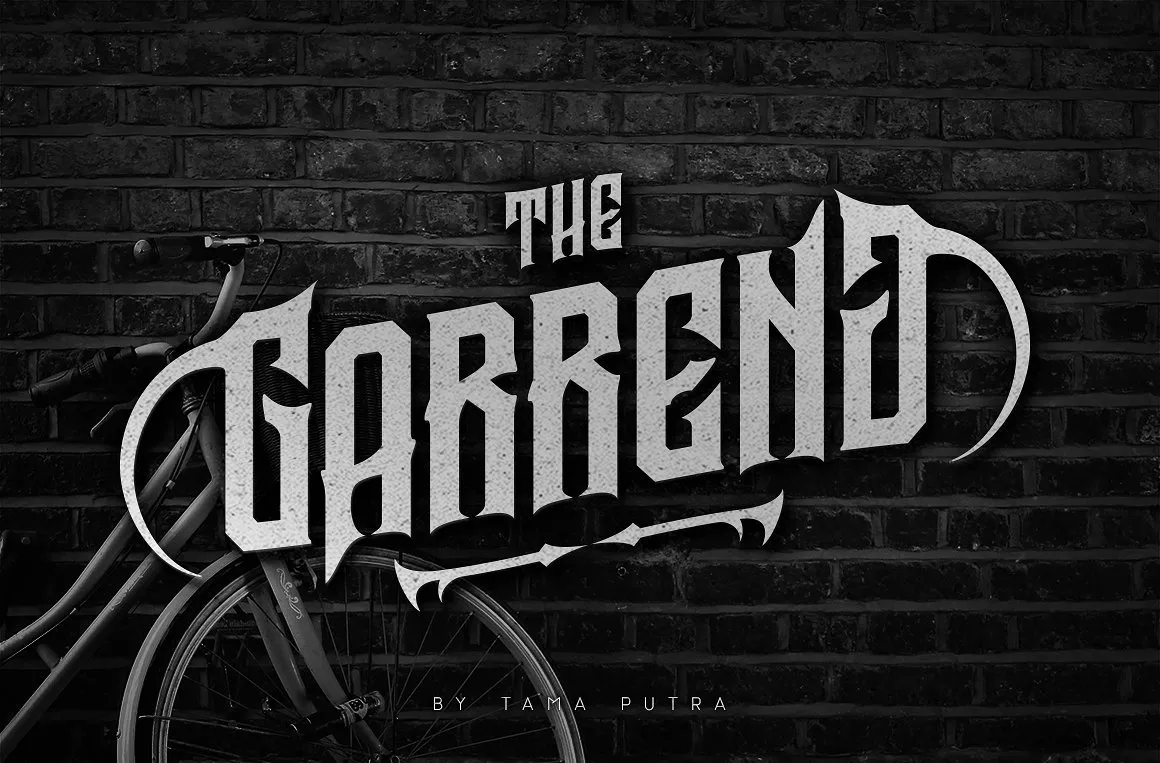
Agradeço pela consulta! Estamos muito felizes por apresentar uma nova tipografia serifada decorativa para você. Introduzimos a Garreng Font! Inspirada no estilo gótico, essa tipo de letra traz um olhar especial aos seus projetos. Garreng é uma fonte completa que inclui todas as letras maiúsculas e minúsculas, suporte multilíngue e de moeda, números, símbolos de pontuação, alternativas, ligaduras e alguns caracteres adicionais. Esta tipografia é perfeitamente adaptada para design visual criativo e artístico. Estamos ansiosos para que você experimente Garreng em seus próximos projetos, seja ele impresso ou digital. É uma adição única a nossa coleção de fontes Display Fonts, cuidadosamente desenvolvida pelo designer Hamilton.